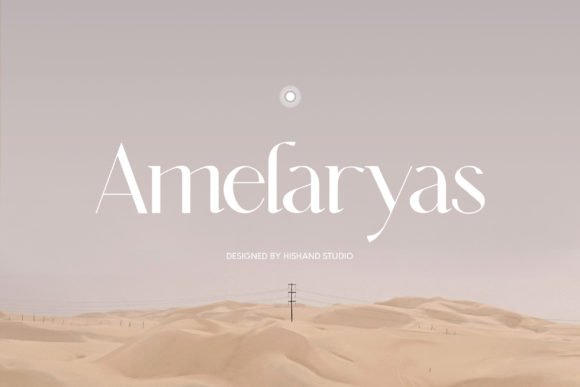
Creativefabrica Amelaryas Font 2021
[Creativefabrica] Amelaryas Font (2021)
Amelaryas - нежный и элегантный шрифт с засечками.
Он прекрасно смотрится на свадебных приглашениях, благодарственных открытках, цитатах, поздравительных открытках, логотипах, визитных карточках и любом другом дизайне, требующем индивидуального подхода.